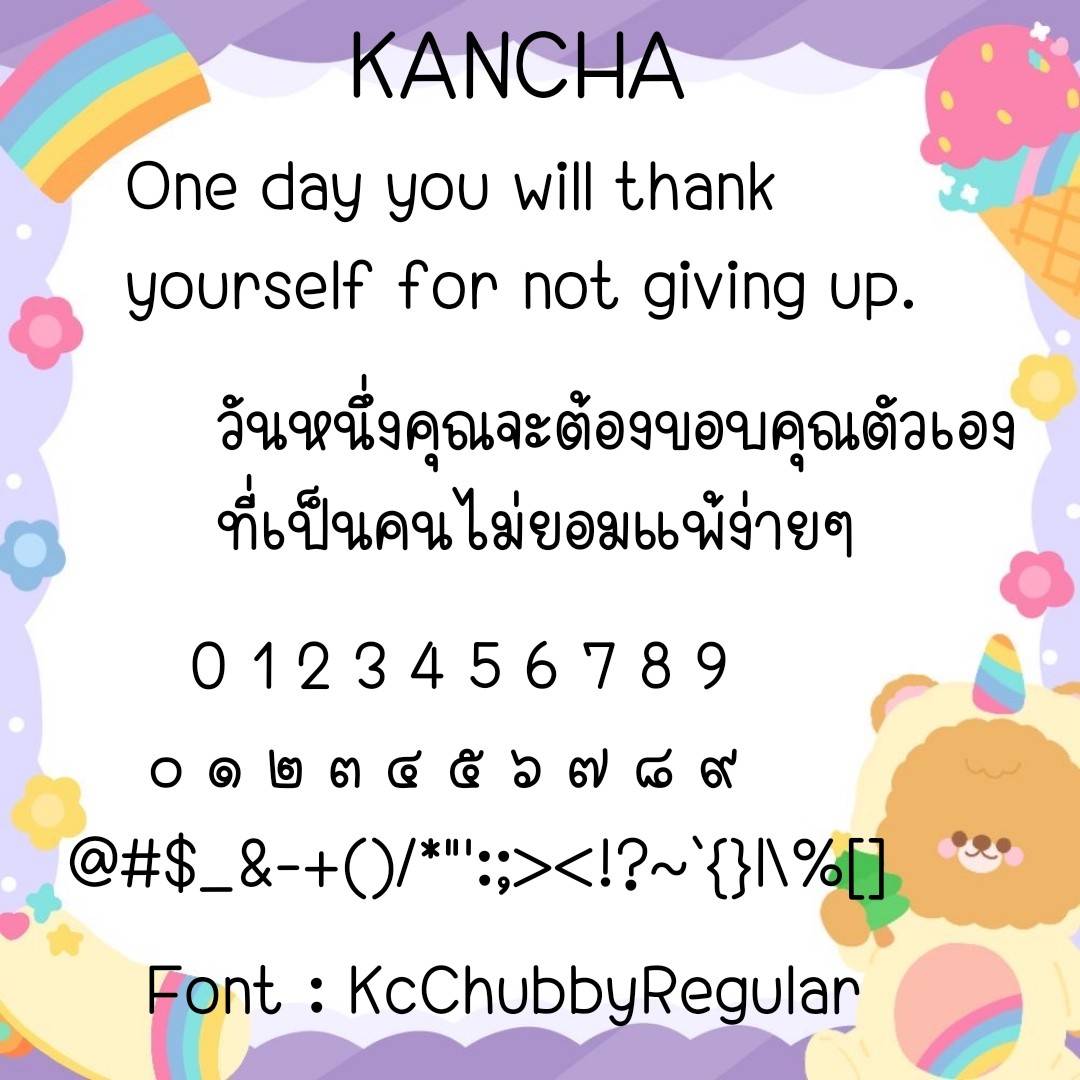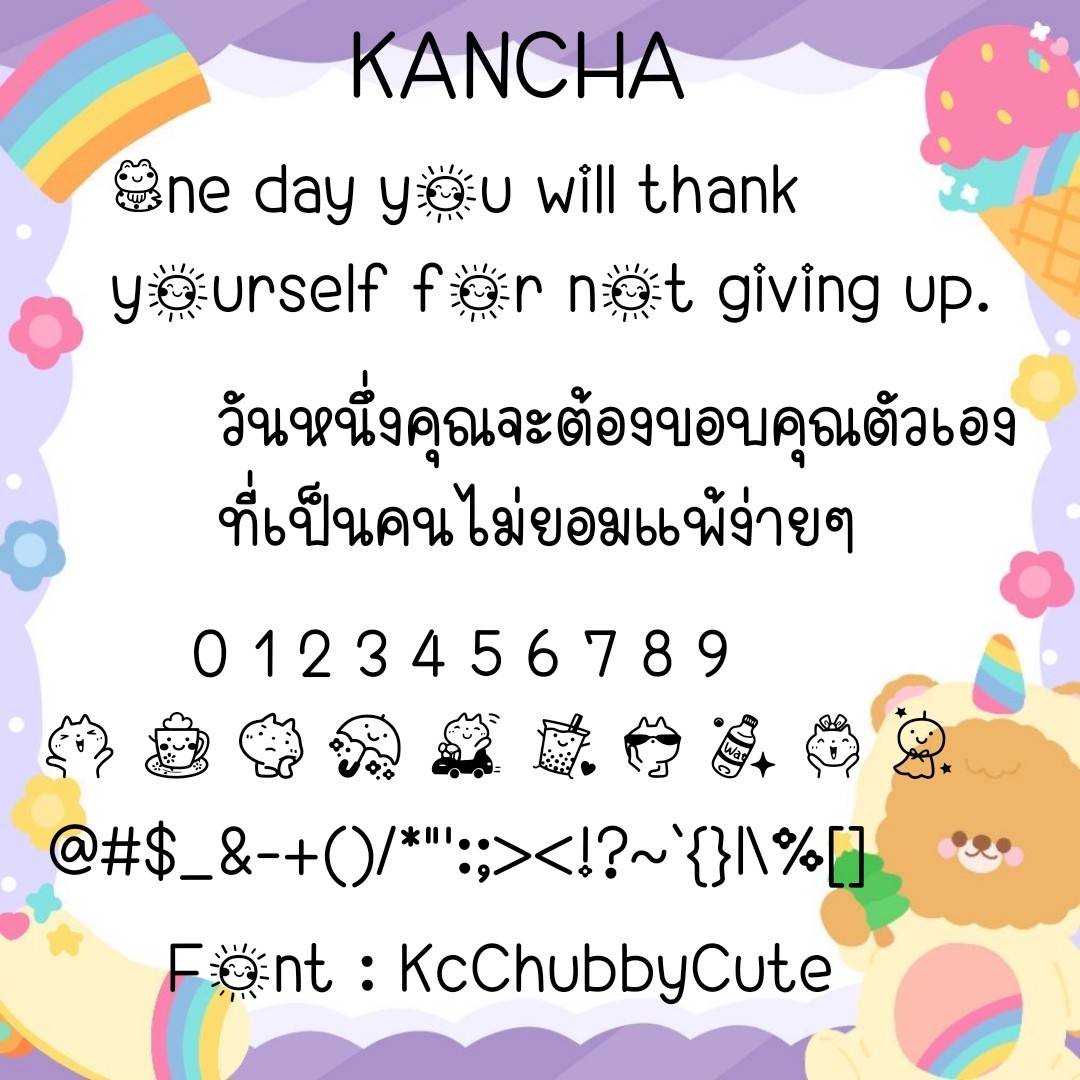
Font KcChubby
ชื่อสินค้า : Font KcChubby 💙
🔸ฟอนต์หัวโตๆ อ่านง่าย น่ารัก สบายตา มีอิโมจิเลขไทยกวนๆในชุดให้ด้วยค่ะ 🥰💙
🔹Big head font, easy to read, cute, comfortable on the eyes. There are emojis of stirring Thai numbers in the set as well.🥰💙